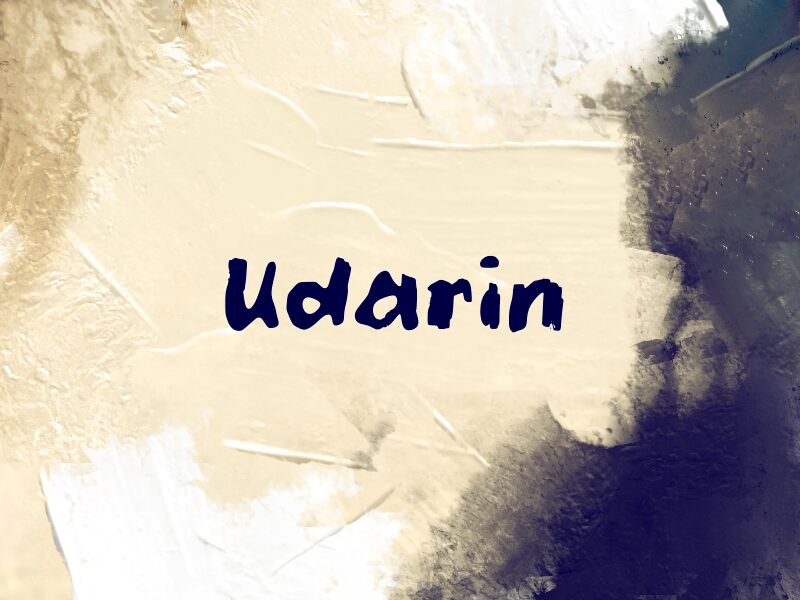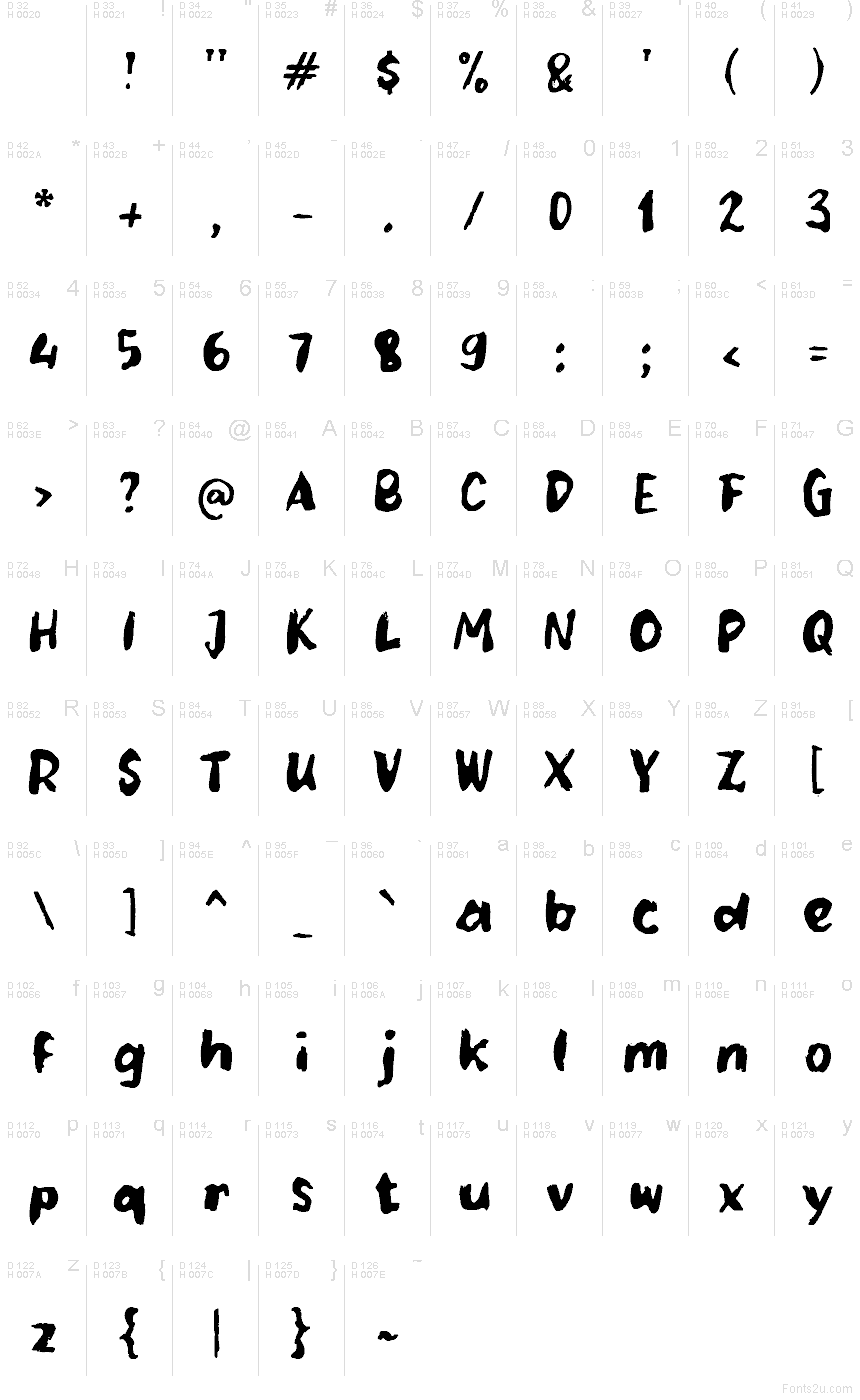
Udarin par Wep est une police brush rough gratuite au rendu massif et peint à la main. Les lettres semblent avoir été déposées sur la page avec un pinceau chargé d’encre, leur conférant des courbes généreuses, des bords francs et de légères irrégularités qui dynamisent le rythme plutôt que de le lisser.
Idéale pour les affiches, les visuels musicaux, le packaging, les couvertures de fanzines ou les cartons de titres, elle apporte ce punch « encre fraîche » indispensable aux textes courts. Disponible gratuitement, Udarin est également parfaite pour des en-têtes percutants ou des monogrammes, car ses formes épaisses conservent tout leur caractère, même dans les mots les plus brefs.
Udarin
Présentation et spécimen de la police Udarin